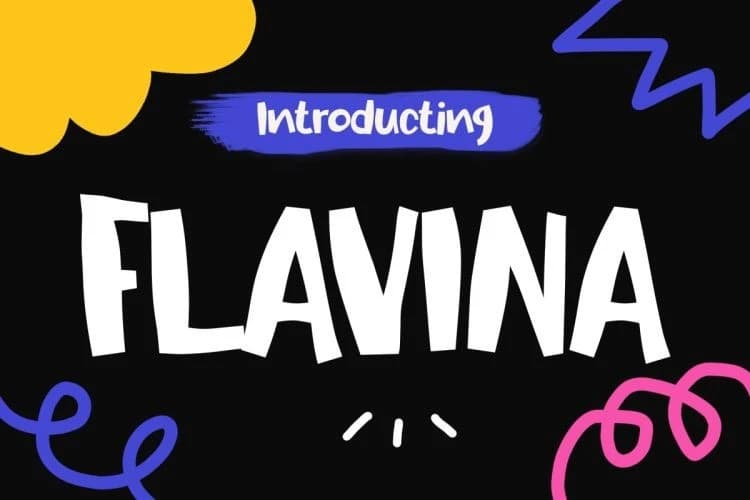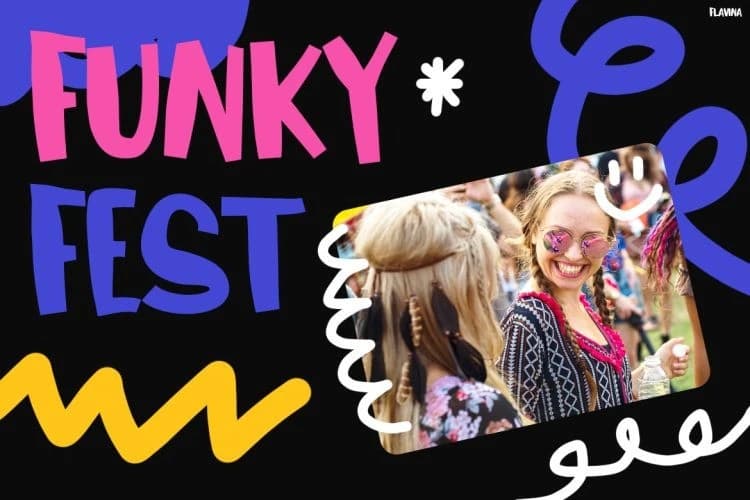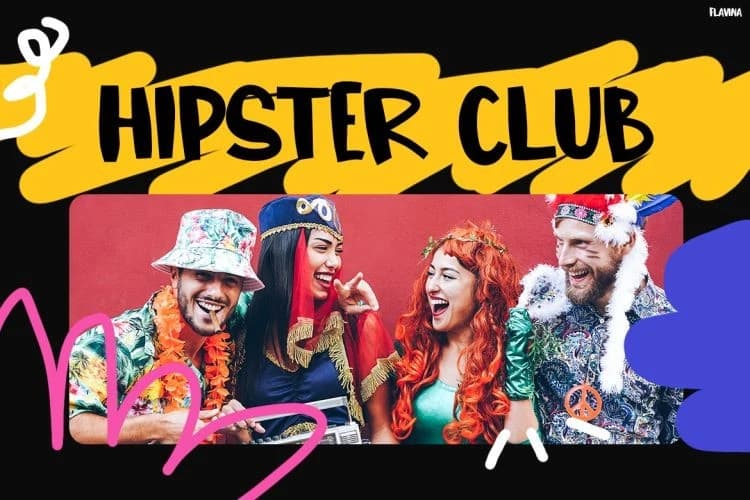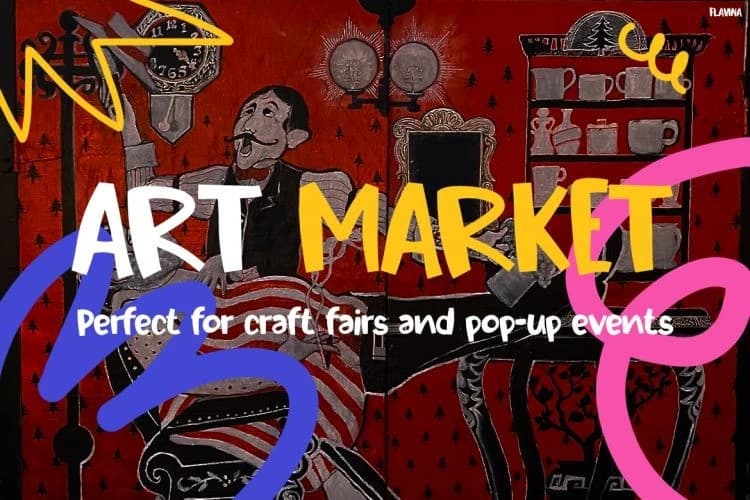
Flavina Playful Font
Flavina Playful Font, renk, enerji ve oyunbaz tavırla patlayan cesur bir gösteri yazı tipidir. Ayrıca kalın hatlı harf biçimleri ve canlı eğrileri, taze ve ifade gücü yüksek bir görünüm oluşturarak öne çıkan bir görsel yaratır.
Flavina Playful Font, kalın ve sıra dışı bir gösteri yazı tipidir; renk, enerji ve oyunbaz tavırla patlar. Ayrıca kalın, iri harf biçimleri ve canlı eğrileri, taze ve ifade dolu bir öne çıkan görsellik yaratır.